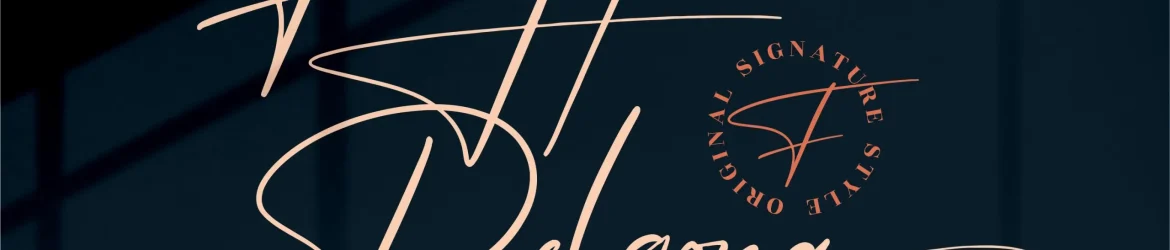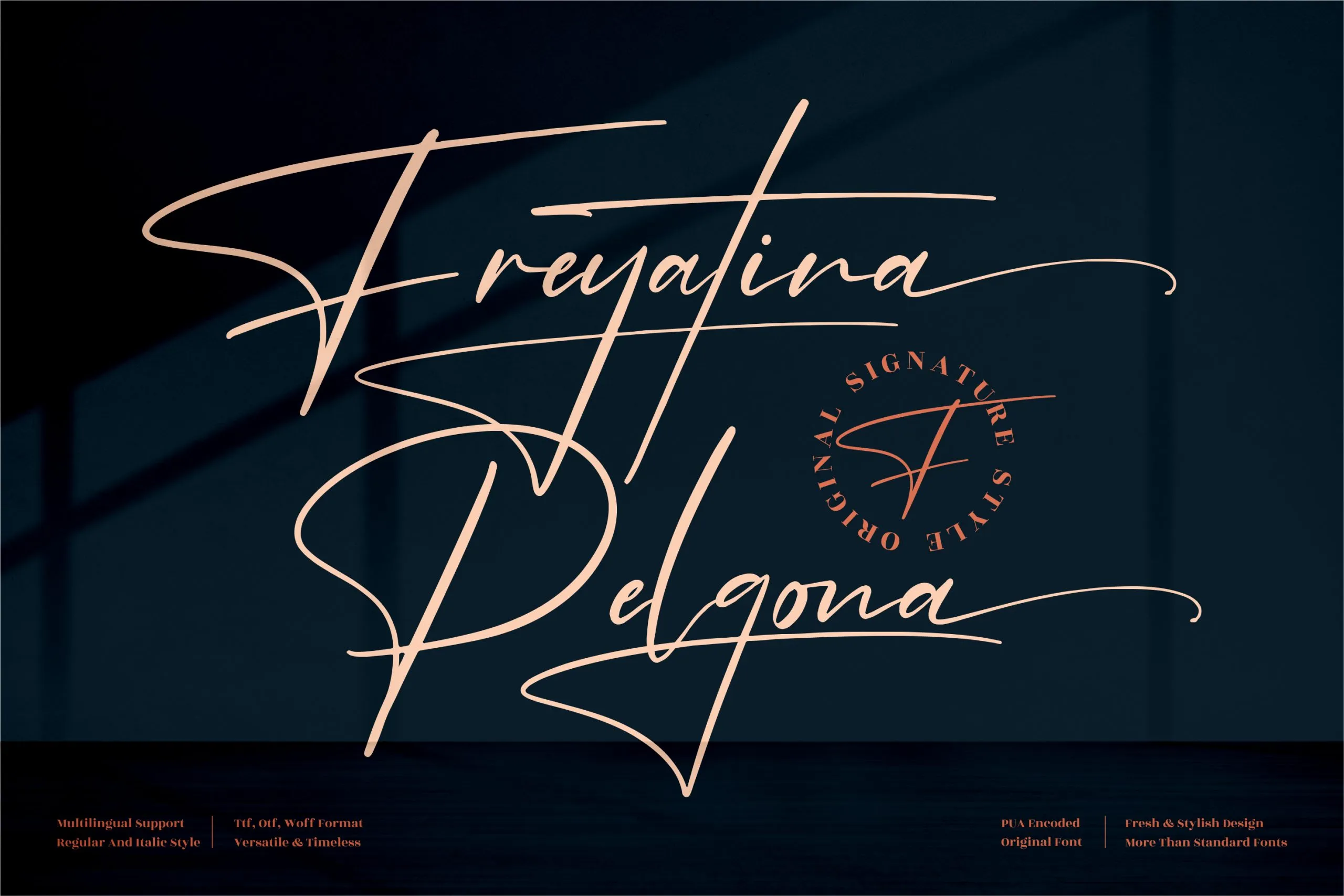
Freyatina Pelgona Font – Fonte Grátis
Freyatina Pelgona Font
A Freyatina Pelgona é uma fonte escrita a mão exclusiva que se destaca por sua elegância e profissionalismo, perfeitamente adaptada para diversos tipos de projetos. Ela traz um toque autêntico e único ao seu trabalho, tornando-a perfeita para criações como logotipos, identidades corporativas, designs de mobília, embalagens de produtos, por exemplo, também é indicada para mugs personalizados, cartões de agradecimento, capas de livros, materiais promocionais e muito mais. A Freyatina Pelgona traz uma qualidade premium que destaca seu trabalho em todas as ocasiões, tornando-a a escolha ideal para projetos de luxo, desde selos até cartazes e embalagens, garantindo sempre um acabamento cuidadosamente meticuloso. Com sua variedade de estilos, essa fonte certamente encaixa-se perfeitamente em qualquer projeto que exige um toque autêntico e sofisticado.